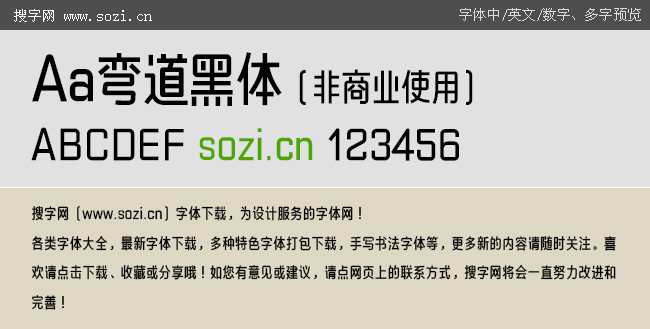
Aa彎道黑體(非商業(yè)使用)
搜字網(wǎng)給大家提供一款A(yù)a彎道黑體(非商業(yè)使用)中文字體下載,這是一款藝術(shù)黑體字體,字體簡(jiǎn)潔大方,并且具有個(gè)性,適合海報(bào)設(shè)計(jì)、包裝畫(huà)冊(cè)等宣傳廣告等應(yīng)用(此字體為個(gè)人非商用版,商用可以聯(lián)系QQ:1006760504)。